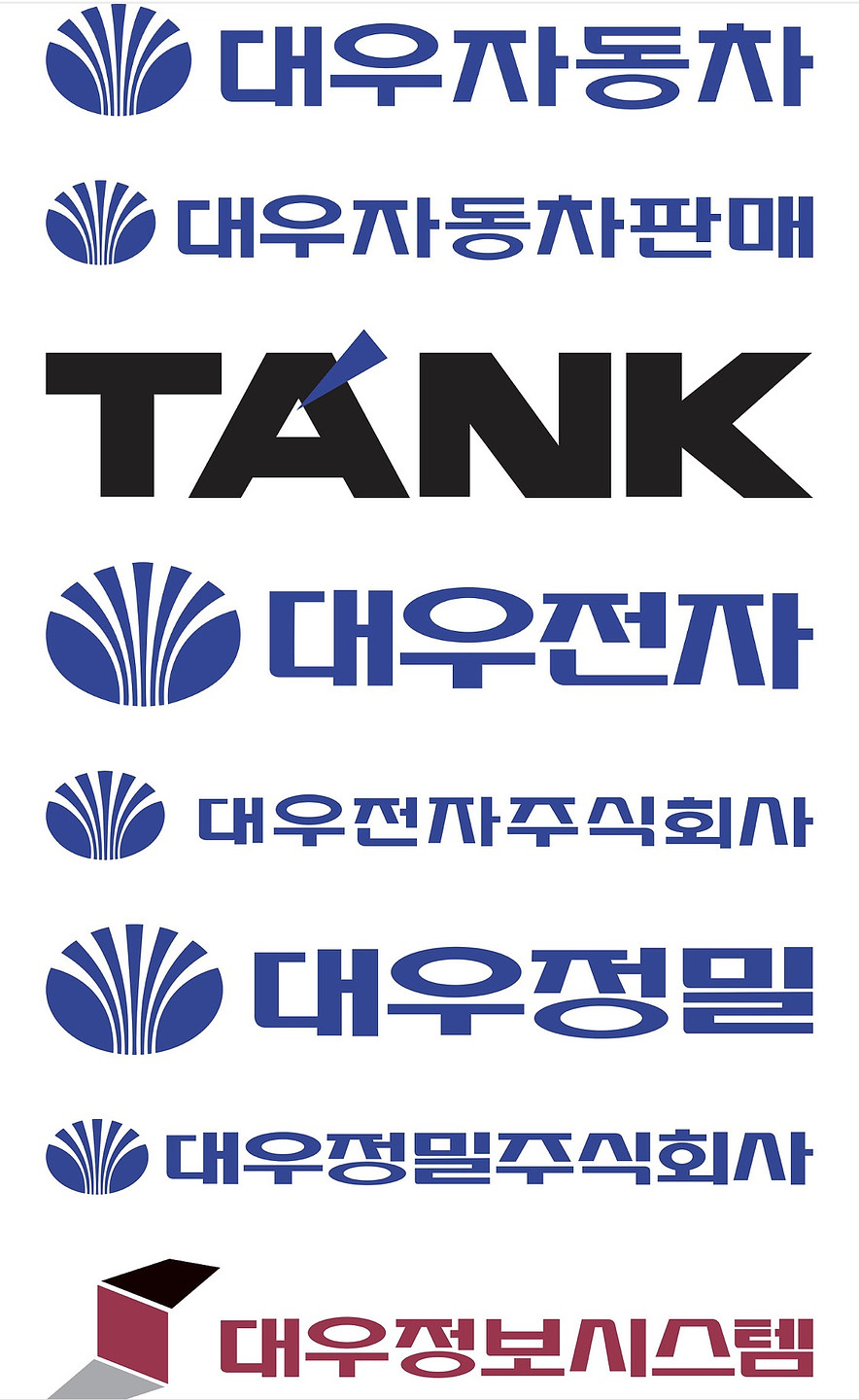
대우그룹 로고입니다. 휴먼매직체와 지하철체라고들 하는데 다들 거짓말이더라고요. 폰트에 대한 정확한 정보가 없네요. 한글과 영어 폰트 이름이 무엇인지, 어디서 구할 수 있는지 아시는 분은 정보 부탁드립니다. 대우 계열사가 50개는 되었는데 일일히 만들지는 않았을거같고 공통적인 폰트가 있는것같습니다..
폰트가 아님
사진을 보면, 대우자동차와 대우전자의 글씨체가 다르고(여기는 “자”字도 겹치는데 완전히 다름), 대우전자와 대우전자주식회사의 “대우전자” 부분의 생김새도 미묘하게 다릅니다. 또, 대우정밀과 대우정보시스템의 “정”자도 미묘하게 다르네요. 폰트를 만들어 쓴 것이 아니라, 계열사마다 일일히 비슷한 서체로 그린 것으로 보입니다.